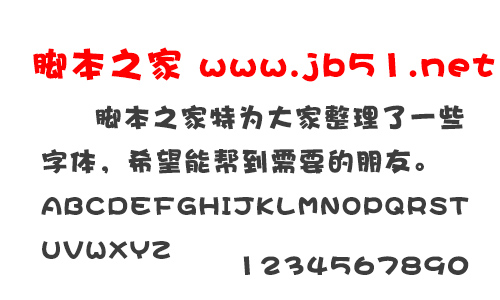
小扣華康海報(bào)是一款非??蓯?ài)的書(shū)法藝術(shù)字體,手寫(xiě)的風(fēng)格圓潤(rùn)的筆畫(huà)讓這款字體看起來(lái)很可愛(ài),筆觸粗細(xì)適中,書(shū)寫(xiě)端正,流暢自然,具有很好的視覺(jué)感,適用于搭配標(biāo)志、廣告標(biāo)語(yǔ)、商業(yè)廣告等高端屬性,歡迎喜歡此字體的朋友前來(lái)下載使用。